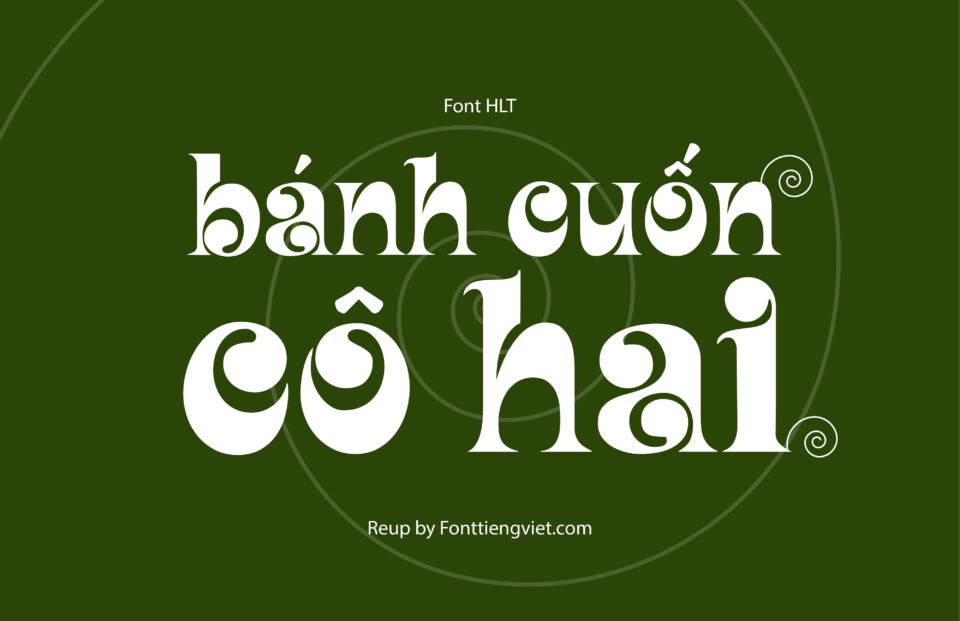
Font Việt hóa HLT Jojo
Giới thiệu về Font Việt hóa HLT Jojo
Trong thế giới thiết kế đồ họa hiện nay, việc lựa chọn một bộ Font Miễn Phí chất lượng là yếu tố then chốt để tạo nên sự khác biệt. Font Việt hóa HLT Jojo nổi lên như một giải pháp hoàn hảo cho những ai yêu thích phong cách trẻ trung, năng động nhưng không kém phần tinh tế. Được chăm chút kỹ lưỡng về đường nét, bộ phông chữ này giúp người dùng dễ dàng truyền tải thông điệp một cách ấn tượng nhất trên các nền tảng số và in ấn.
Đặc điểm nổi bật của bộ font chữ này
Font Việt hóa HLT Jojo sở hữu cấu trúc các ký tự tròn trịa, tạo cảm giác thân thiện và dễ gần cho người xem. Đây là kiểu chữ cực kỳ phù hợp cho các poster sự kiện, bìa sách thiếu nhi hoặc các bài thuyết trình tại trường học. Khả năng hiển thị tiếng Việt trọn vẹn, không lỗi dấu chính là ưu điểm lớn nhất, giúp các bạn học sinh và giáo viên tiết kiệm thời gian chỉnh sửa văn bản.
Ứng dụng Font Việt hóa HLT Jojo trong học tập và công việc
Việc sử dụng Font Việt hóa HLT Jojo mang lại hiệu ứng thị giác mạnh mẽ cho các sản phẩm sáng tạo. Bạn có thể dùng font này để thiết kế thiệp chúc mừng, làm video clip ngắn hoặc trang trí các dự án thủ công. Với tính linh hoạt cao, bộ chữ này không chỉ làm đẹp giao diện mà còn tăng cường khả năng nhận diện nội dung nhờ độ tương phản tốt giữa các nét thanh và nét đậm.
Lưu ý khi sử dụng font chữ
Dù là một phông chữ đẹp, người dùng nên kết hợp nó với các phông chữ không chân khác để tạo sự cân bằng cho bố cục. Hãy đảm bảo kích thước chữ đủ lớn để phát huy tối đa vẻ đẹp của các đường cong đặc trưng trong thiết kế này.